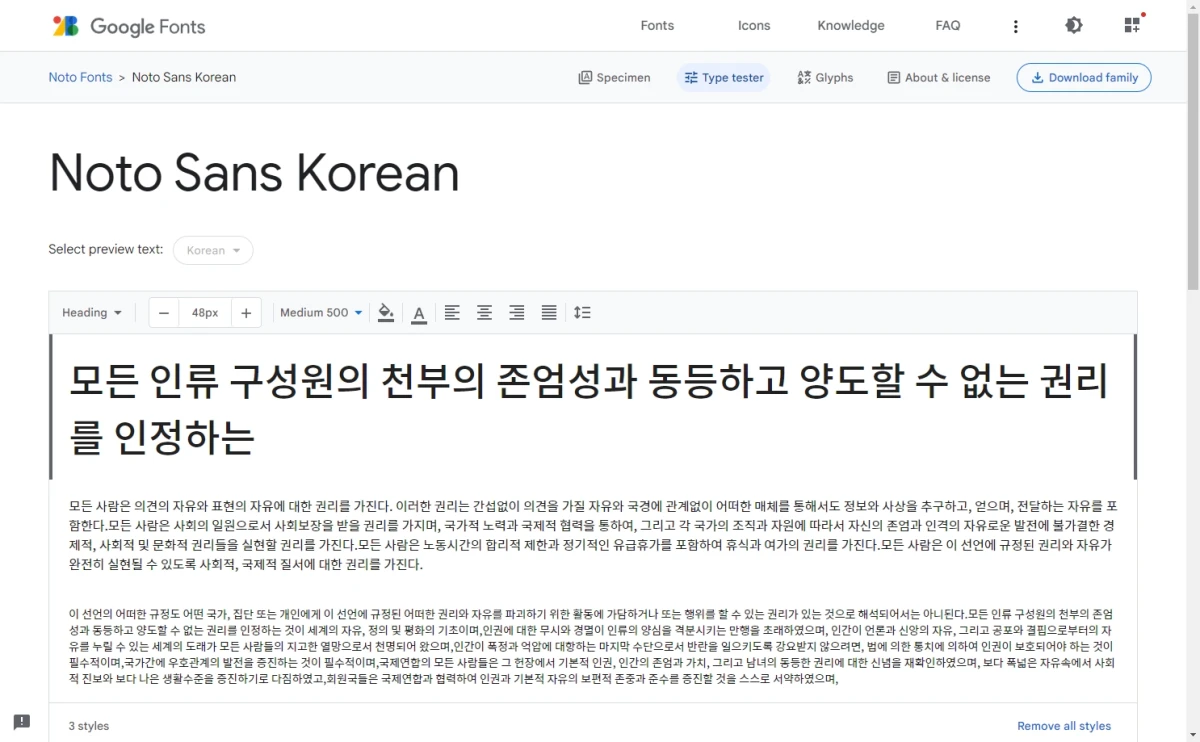
웹사이트 제작에 필요한 웹폰트 모음
웹사이트 가독성을 높이는 한글, 영문 웹폰트를 비교해 Noto Sans KR, 나눔고딕, Roboto 등 실무에서 자주 쓰는 서체를 정리했습니다. Noto Sans Korean, Nanum Gothic, Open Sans, Roboto, Lato 등을 다룹니다.
Noto Sans Korean
구글이 2012년부터 개발하기 시작한 오픈 소스 글꼴인 '노토 산스'의 한글 지원 문자입니다. 개발에 참여한 어도비에서는 '본고딕' 혹은 'Source Han Sans'라는 명칭으로 배포합니다.
Nanum Gothic
나눔고딕은 네이버에서 무료 배포하는 글꼴로 웹폰트로도 많이 쓰입니다. 글꼴의 모서리가 약간 둥글둥글한 점이 굴림체와 유사합니다.
Open Sans
널리 사용되는 영문 폰트이며 한글 웹사이트에서도 기본 글꼴로 많이 쓰입니다.
Roboto
구글에서 개발하여 안드로이드 시스템 폰트로 사용하였고 현재 영문 웹폰트로 인기가 높습니다. 특히 가독성이 높으면서 많은 정보를 전달할 수 있는 폰트입니다.
Lato
영문 웹사이트에서 기본 글꼴로 많이 사용하며 깔끔하면서도 유연하고 읽기 쉬운 특징을 가지고 있습니다.
Montserrat
깔끔하고 선명한 느낌이 강한 산세리프 폰트로, 적절한 굵기와 너비로 가독성이 높습니다.